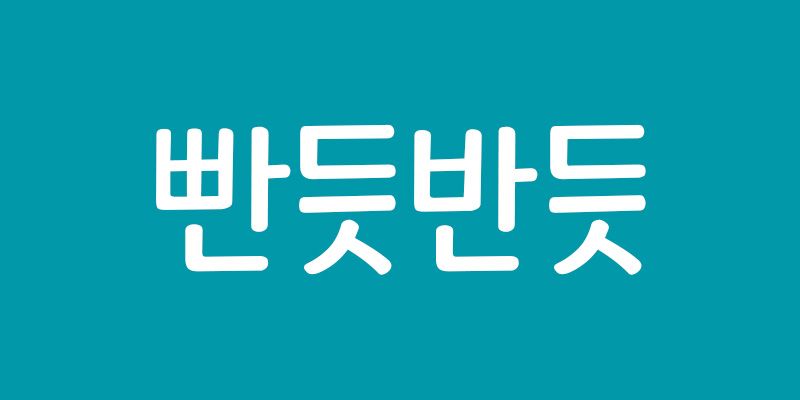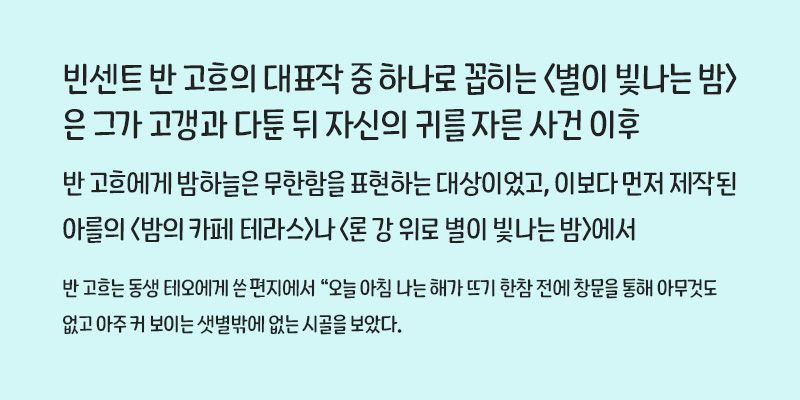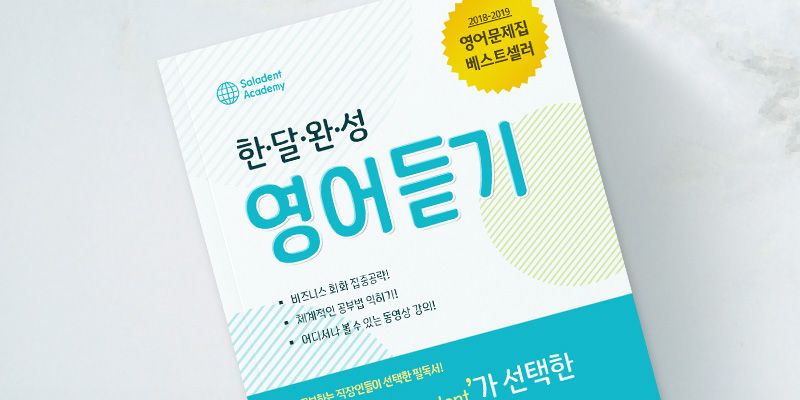
RixStraight ist eine Handschrift mit einem ordentlichen und organisierten Eindruck. Die feinen Abrundungen der Ecken lassen die Schrift weich erscheinen, und die Zeichen in verschiedenen Größen wirken rhythmisch aufeinander abgestimmt. Die geordneten Linien machen die Schrift sehr gut lesbar.